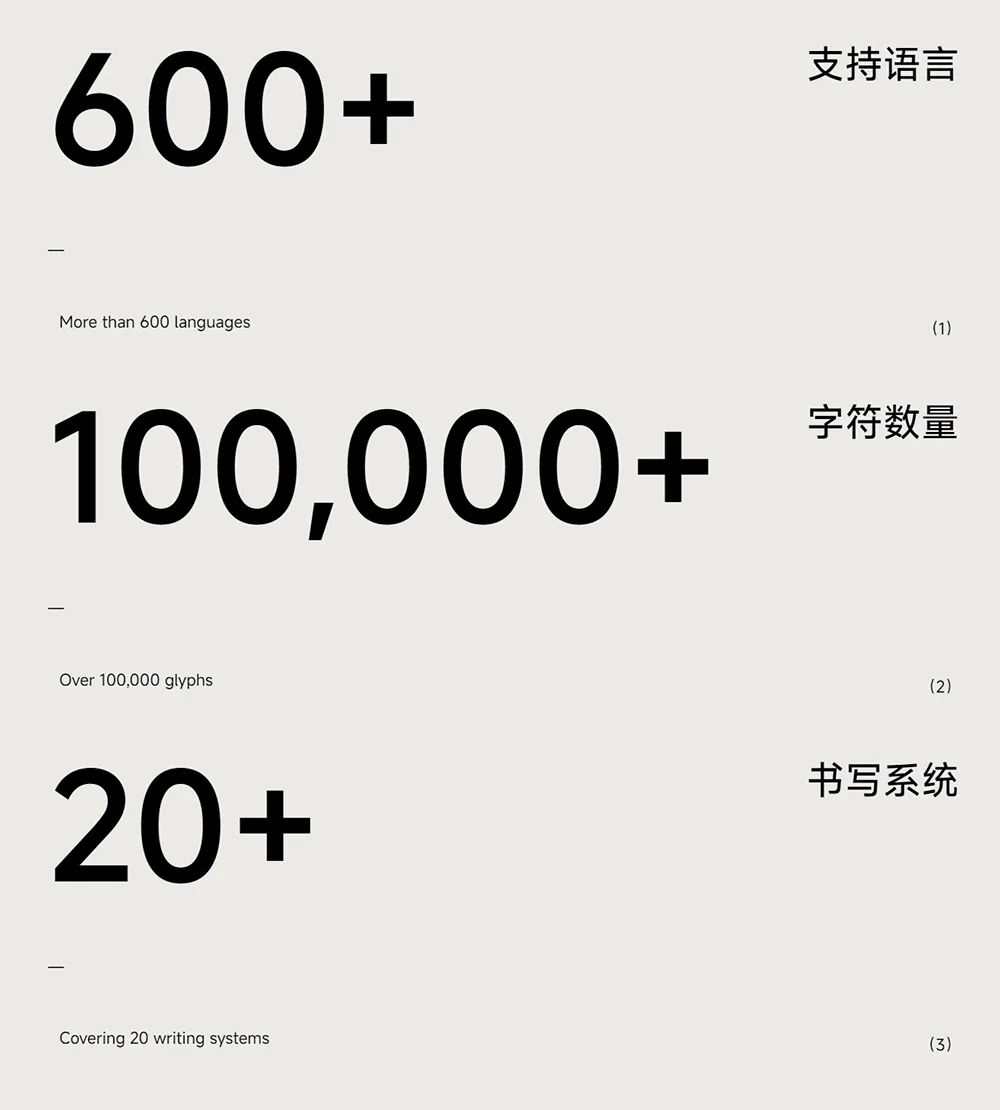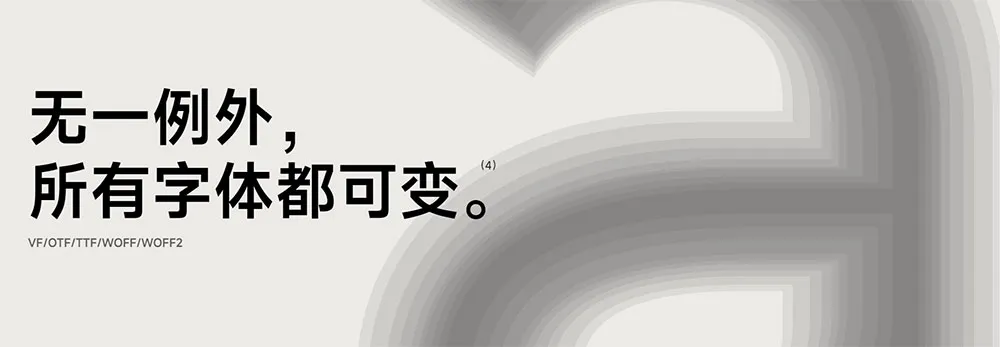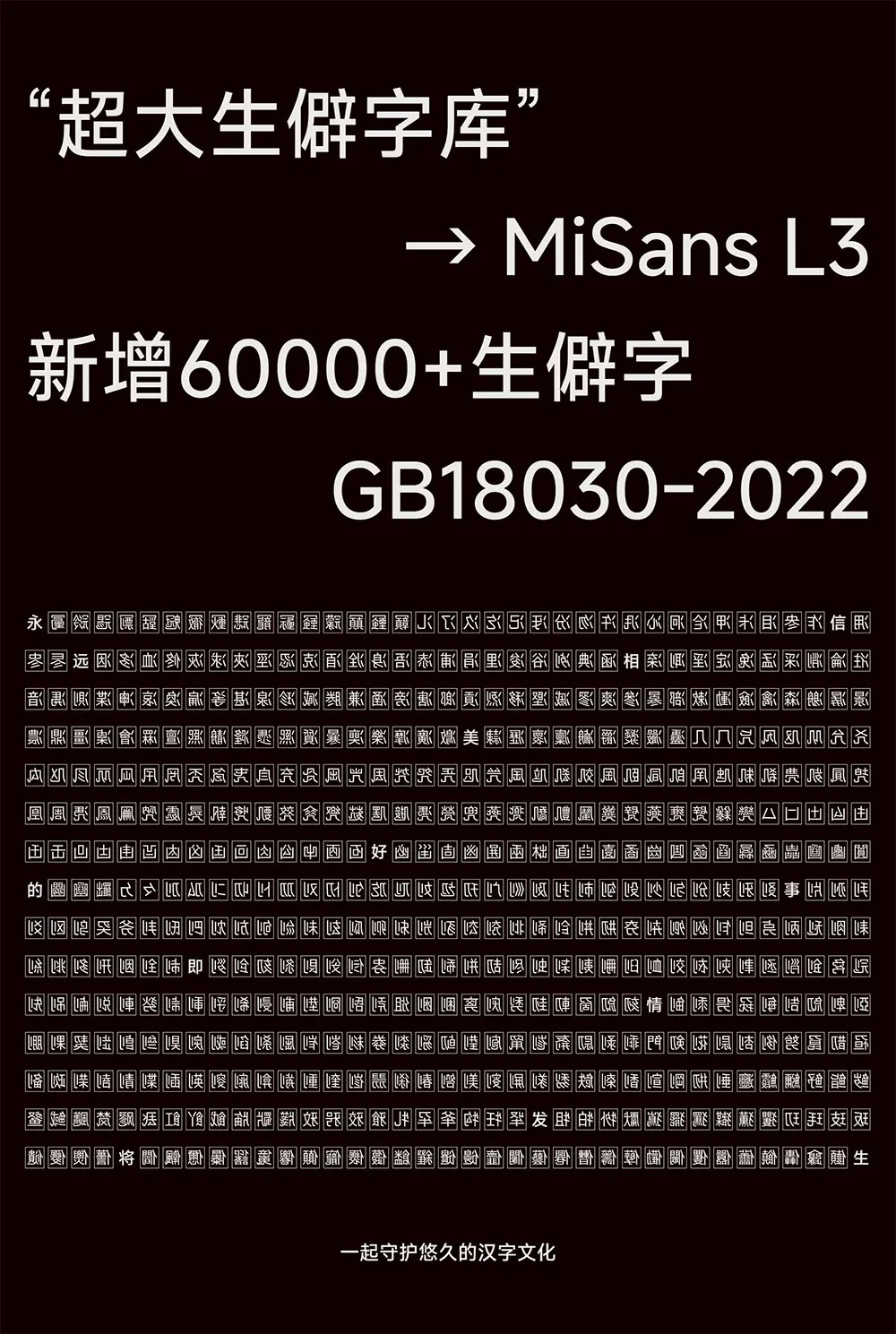
MiSans介紹
2021 年在 MIUI 13 中推出全新系統字體 MiSans;字體規格、細節全方位升級並加入了豐富的 OpenType Features,並在發佈當天宣佈該字體面向全社會免費商用。
2023 年在全新系統 Xiaomi HyperOS 中推出全球語言定製字體項目— MiSans Global。這是一個龐大的字體家族,涵蓋 20 多種書寫系統,支持 600 多種語言,字符數量累計超過10萬個。
MiSans Global 是由小米主導,聯合蒙納字庫、漢儀字庫共同打造的全球語言字體定製項目。這是一個龐大的字體家族,涵蓋 20 多種書寫系統,支持 600 多種語言,字符數量超過 10 萬個。作為 Xiaomi HyperOS 系統默認字體,我們以簡約/清晰,人文/易讀,統一的視覺風格為基本原則出發,構建多語言信息體驗一致性,旨在幫助為 Xiaomi HyperOS 提供互聯的通用體驗。
超大生僻字庫,MiSans L3,新增60000+生僻字,符合 GB18030-2022 最新字符集國家標準
GB18030-2022 強制規範三個實現級別,於 2023 年 8 月 1 日起開始執行。實現級別1共 27,584個漢字;實現級別 2 包含實現級別 1,此外,實現級別 2 還支持《通用規範漢字表》中的沒有包含在實現級別 1 之內的編碼漢字,共計 27,780 個漢字;實現級別 3 包含實現級別 2,此外,實現級別 3 還支持新標準件規定的全部漢字及表 3 中的康熙部首,總計 87,887 個漢字,用於政務服務和公共服務的產品應滿足實現級別 3 的要求。 MiSans 包含級別 1+ 級別 2,MiSans L3 為級別 3 字庫(該字庫不包含級別 1 和級別 2)。MiSans 包含級別1+級別2,MiSans L3 為級別3字庫(該字庫不包含級別1和級別2)
MiSans 不僅服務於數以億計的小米移動設備用戶,所有公眾也都可以免費使用這款字體。自 2021 年底字體發佈以來,越來越多的個人和企業選擇在品牌、系統設計和商業案例中使用 MiSans。同時,我們也在不斷完善和更新 MiSans 字體,包括增加更多的語言和文字,覆蓋更多的常用漢字,讓所有人在使用 MiSans 時都能得到最好的體驗。
甚麼是可變字體?
可變字體是 OpenType 在 1.8 版規範中引入的擴展規範,簡單說明就是一個字體文件同時支持多個字體形態,可以將多個字體文件合在單個字體文件中,通過定義字體內的變化來實現單軸或多軸設計空間。
是否所有字體都支持可變?
MiSans L3 生僻字字庫(GB18030-2022 級別3)僅支持 Regular 字重。 其他所有字體均支持可變。
MiSans Global 在 Xiaomi HyperOS 中的進版計劃
MiSans Global 的製作分工
由小米主導,聯合蒙納、漢儀共同製作完成。其中蒙納負責泰語、老撾及印度的所有地區語言。漢儀負責繁體中文、阿拉伯語、藏文、緬甸、高棉。